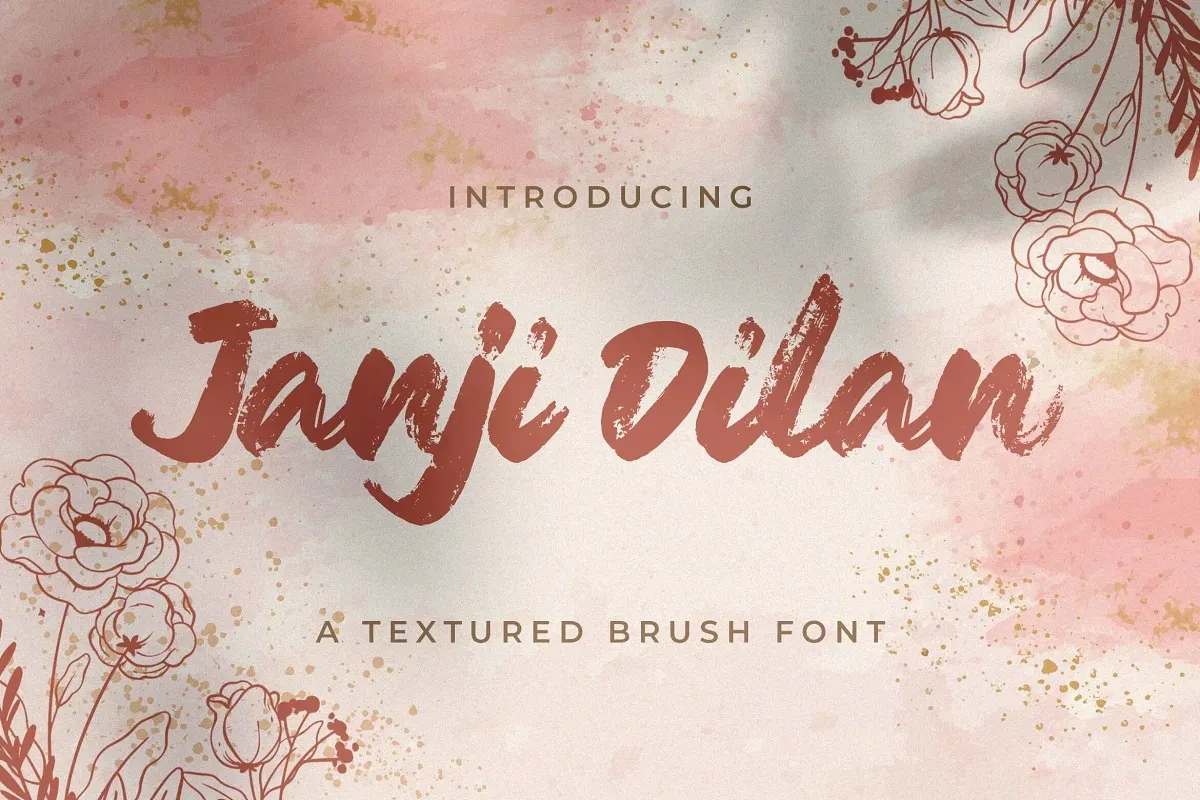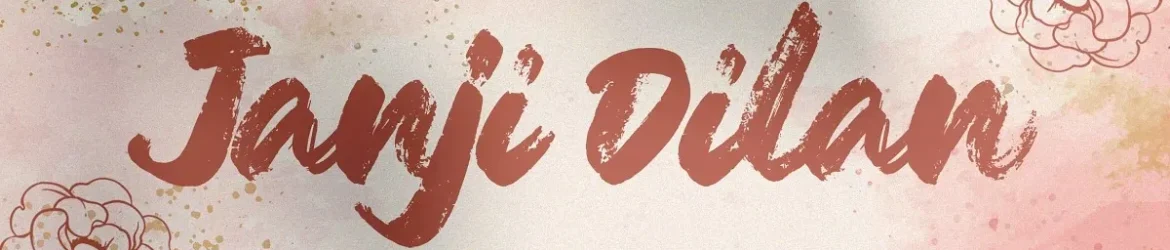
A fonte Janji Dilan é uma opção elegante para projetos que exigem estilo moderno e força. Desenvolvida pelo StringLabs em 99designs, ela se destaca por suas linhas afiadas e vigorosas, com traços aparentemente rápidos e fáceis de secar. Seu design é perfeito para criações que exigem forte impacto visual, como projetos de marca, designs de móveis de casa e embalagens de produtos. Além disso, Janji Dilan também se adapta bem ao uso de textura sobre qualquer imagem de fundo, tornando-se uma excelente opção para estilos criativos e contemporâneos.